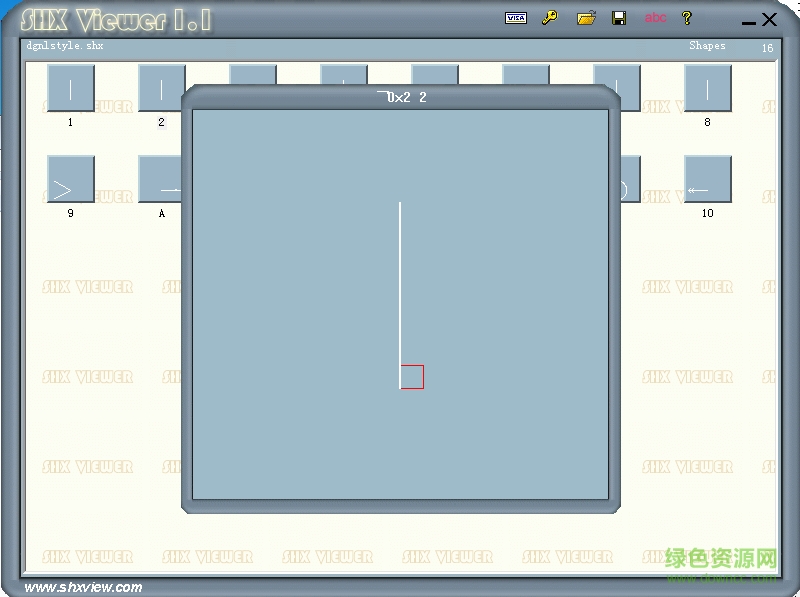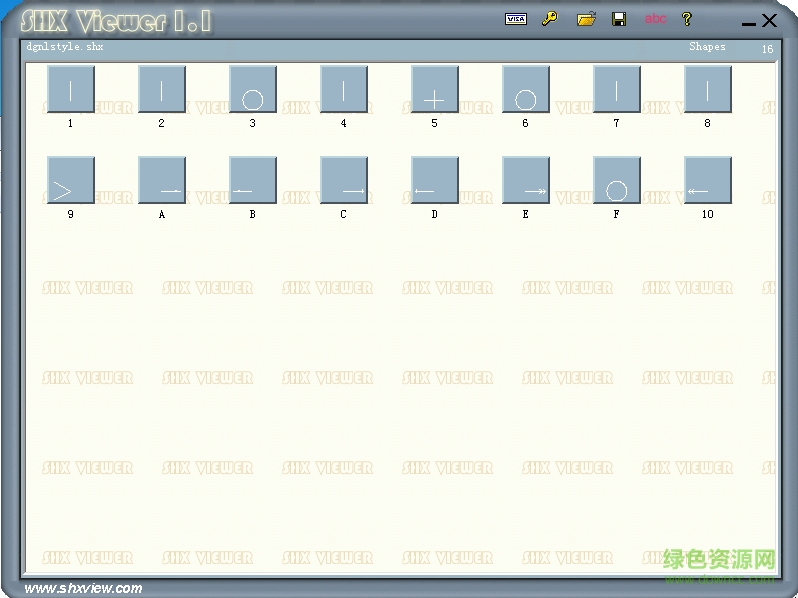
dgnlstyle.shx是CAD軟件中使用的shapes字體,擁有少量字符,包括支線(xiàn)、圓圈、箭頭等,常用語(yǔ)文字或數(shù)字標(biāo)記,歡迎大家下載使用!
cad里所稱(chēng)的shx字體和大字體(也叫bigfont),都是autocad專(zhuān)用專(zhuān)有的字體。大字體也是shx字體,是shx字體的一種特殊形式。
用shx字體做的文件相對(duì)會(huì)更小,顯示速度快,shx字體為線(xiàn)型字體,有線(xiàn)的屬性,可以更改線(xiàn)的厚度值,產(chǎn)生立體效果。
autocad有自己的字庫(kù),在fonts目錄里。字體文件以shx為擴(kuò)展名,稱(chēng)為shx字體。最初的shx字體支持的是ANSI字符,后來(lái)擴(kuò)大到支持非ANSI字符,也就是大字體或bigfont,用雙字節(jié)儲(chǔ)存,這也就是為什么叫大字體的原因。